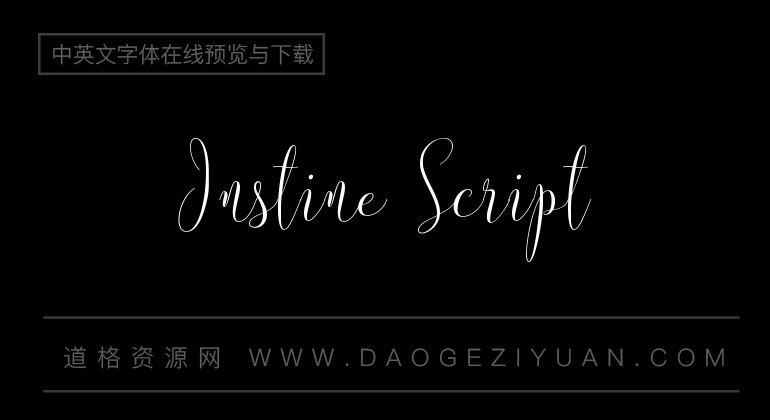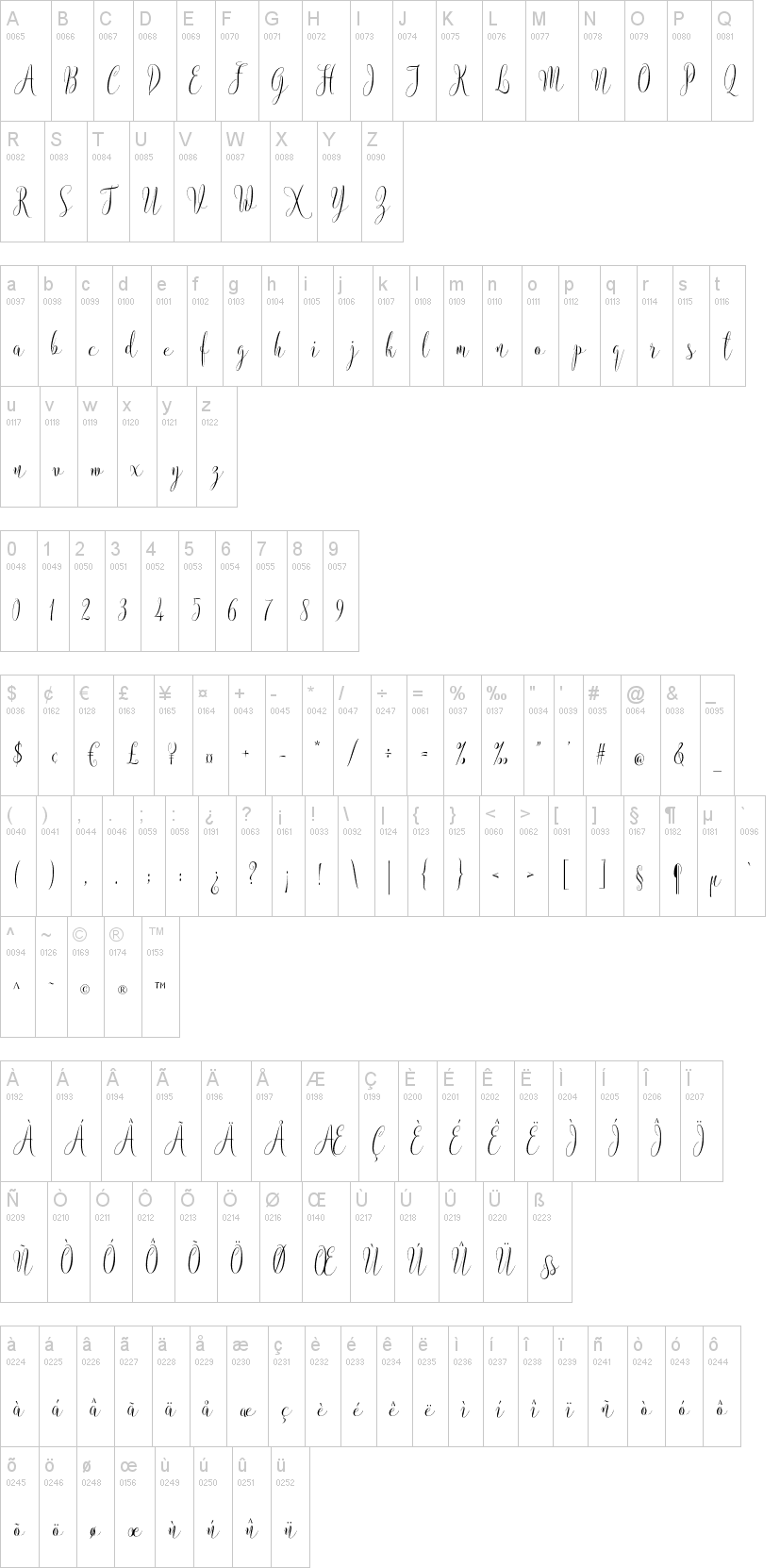
Instine Script
Instine Script 是一种西文手写体字体,它是由著名的字体设计师 Brian J. Bonislawsky 创作的。这种字体是以古典手写体为基础,采用现代字体技术,融合了西班牙、意大利和法国的元素,使其具有优雅的外观。Instine Script 的字形设计精细,有着细腻的线条和流畅的曲线,使得它在文字中具有非凡的表现力。它适用于大多数文字应用,如书籍、广告、海报、网站等,是一种非常优秀的字体。
Instine Script是一款非常不错的手写艺术字体,具有很好的视觉感,适合于文化类的宣传设计、商业类品牌的广告和产品包装设计以及个性化文字排版等较多场景。
Instine Script字符映射图